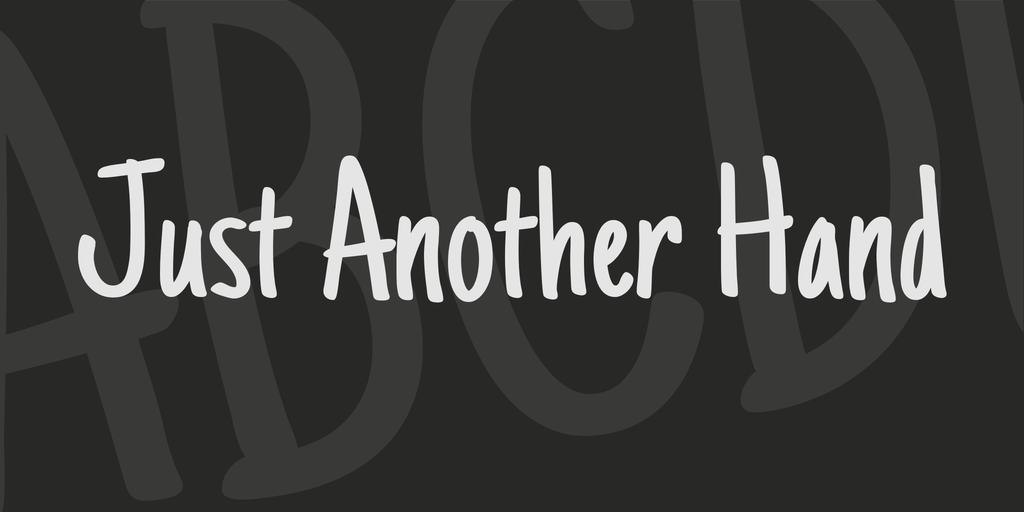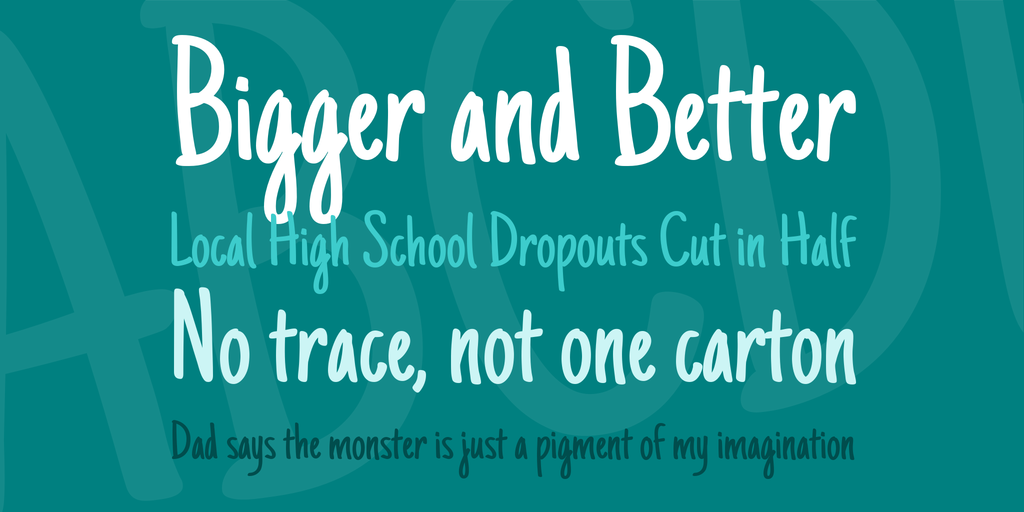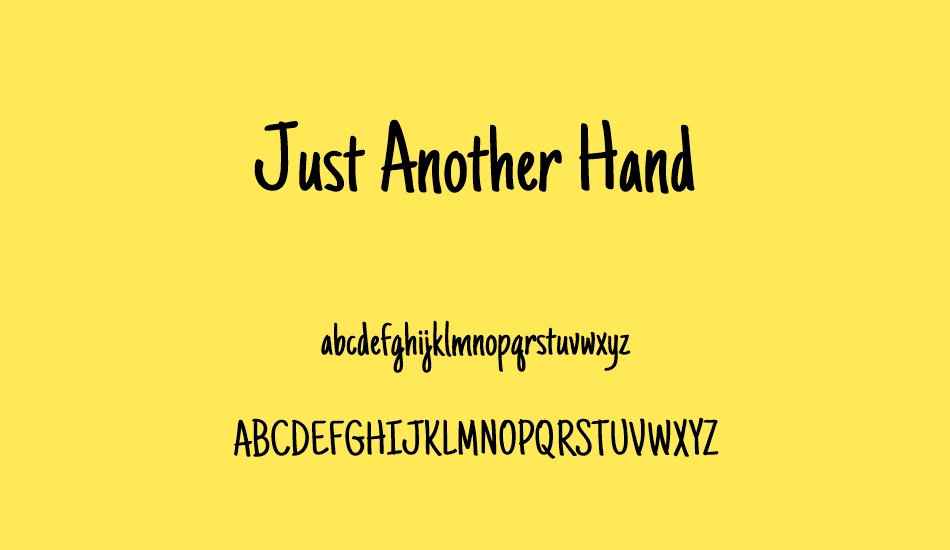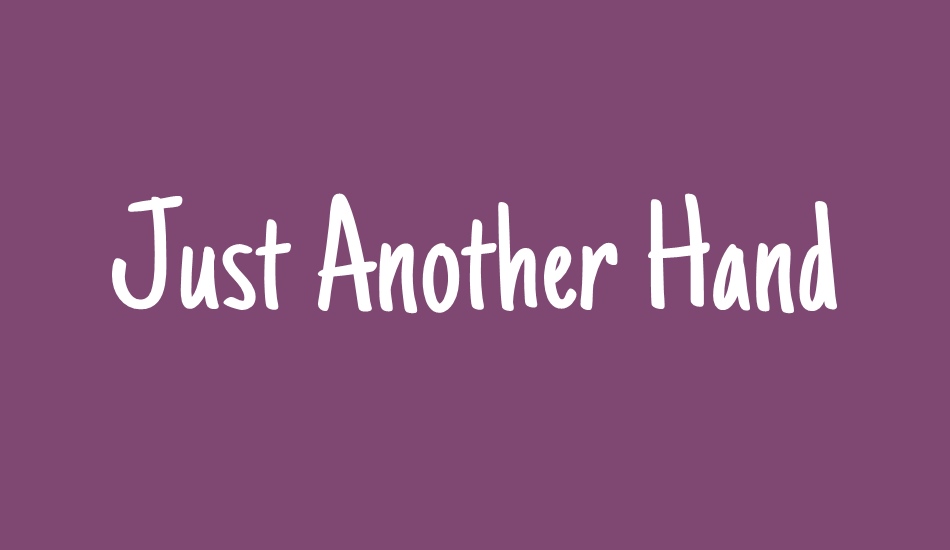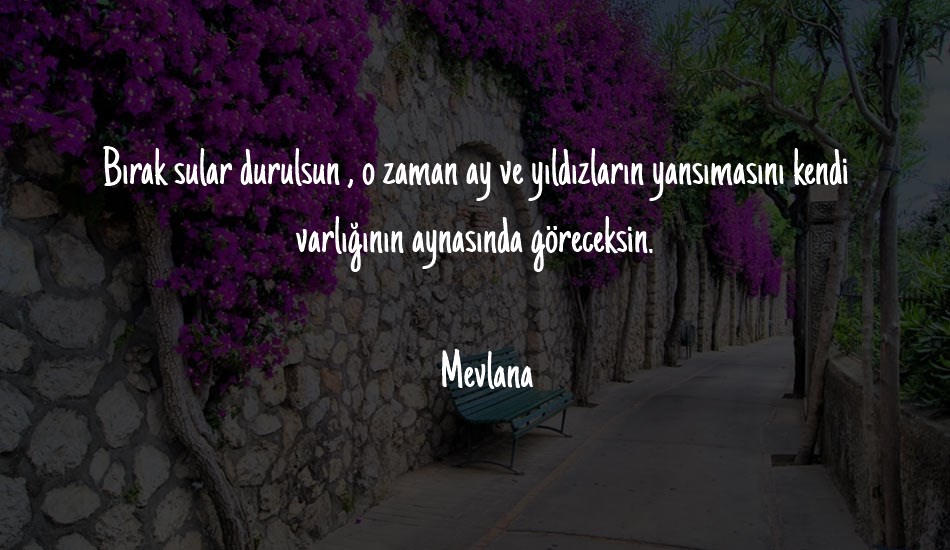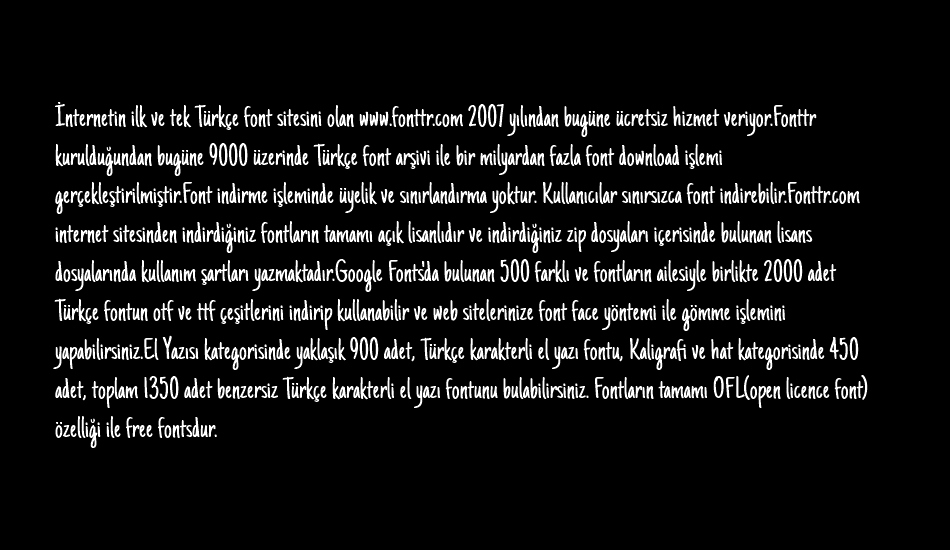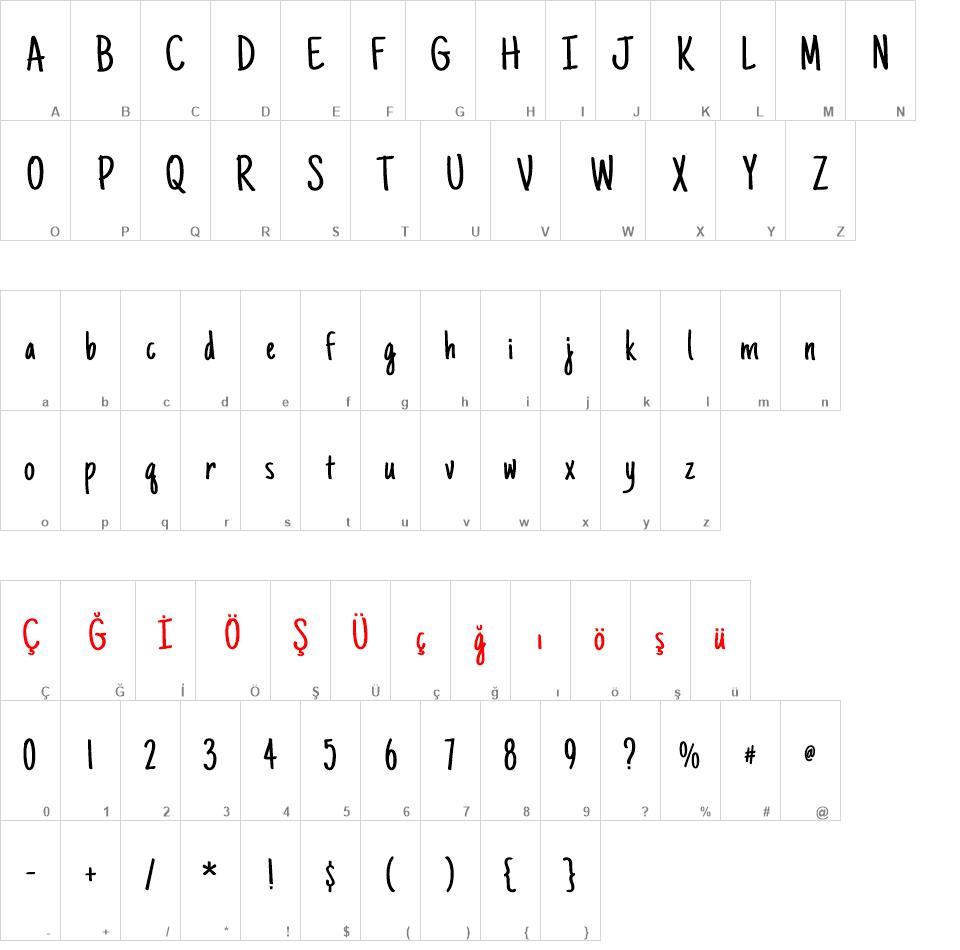
Kişisel el yazımız yıllar içinde birçok kez değişti. Just Another Hand, lise günlerimin elyazısından esinlenilerek dar bir fırça çizilmiş elyazısı yazı tipidir. Lisede bir fırça ile yazmadığım halde, bu yorum için daha temiz bir vuruş istedim anlamında, Bir Başka Elle alınan küçük bir sanatsal lisans var.
Küçük bir kişilik, küçük bir kısıtlama ... genelinde her türlü projede çalışan bir stil.